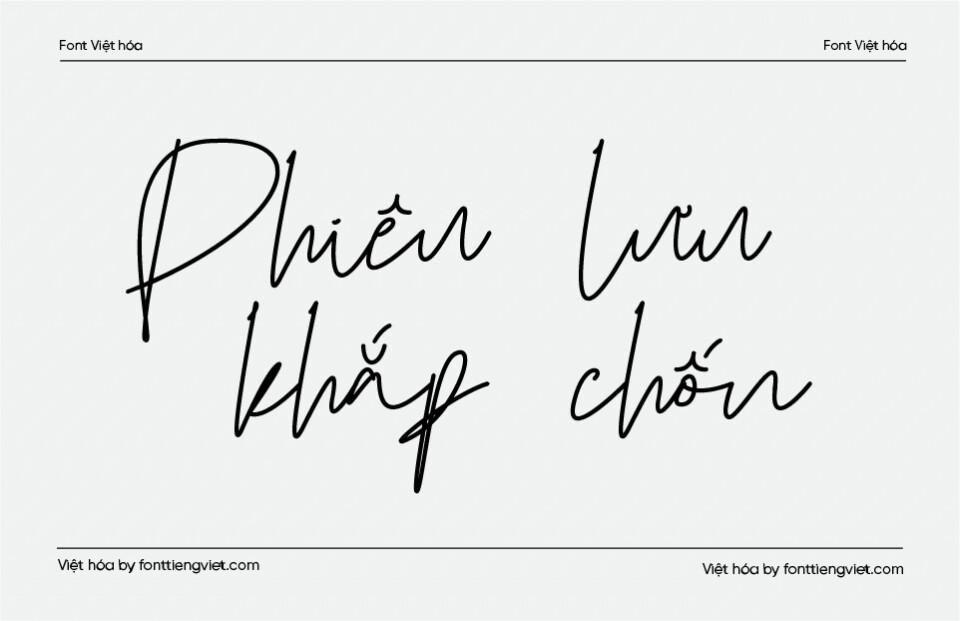
Trong thế giới thiết kế đồ họa, việc lựa chọn Font Chữ phù hợp có vai trò cực kỳ quan trọng, đặc biệt khi bạn muốn tạo ra sự tinh tế và cá nhân hóa cho các ấn phẩm đặc biệt. Đối với thiệp cưới, thiệp mời hay các tài liệu mang dấu ấn cá nhân, một font chữ viết tay đẹp mắt có thể nâng tầm giá trị thẩm mỹ lên một tầm cao mới. Và đó chính là lý do vì sao Font Việt hóa 1FTV VIP Kalmost – Chữ Ký Viết Tay Tinh Tinh Tế Cho Thiệp Cưới & Thiệp Mời lại trở thành lựa chọn hàng đầu của nhiều nhà thiết kế và cặp đôi. Font chữ này không chỉ mang đến vẻ đẹp mềm mại, uyển chuyển của nét chữ ký tay mà còn được Việt hóa hoàn chỉnh, đảm bảo trải nghiệm sử dụng mượt mà với ngôn ngữ tiếng Việt.
Khám Phá Sự Tinh Tế Của Font Việt hóa 1FTV VIP Kalmost – Chữ Ký Viết Tay Tinh Tế Cho Thiệp Cưới & Thiệp Mời
Bạn đang tìm kiếm một font chữ độc đáo, có khả năng thể hiện sự sang trọng, lãng mạn và mang đậm dấu ấn cá nhân? Font 1FTV VIP Kalmost chính là câu trả lời. Được thiết kế dựa trên cảm hứng từ những nét chữ ký tay tự nhiên, font chữ này sở hữu sự mềm mại, uyển chuyển khó cưỡng. Từng đường nét đều được chau chuốt tỉ mỉ, tạo nên một tổng thể hài hòa, dễ đọc nhưng vẫn giữ được chất nghệ thuật riêng. Đặc biệt, việc font được Việt hóa hoàn chỉnh là một điểm cộng lớn, giúp người dùng dễ dàng sử dụng tiếng Việt mà không gặp bất kỳ lỗi hiển thị hay mất ký tự nào. Điều này cực kỳ quan trọng đối với các ấn phẩm như thiệp cưới, thiệp mời sinh nhật hay các văn bản cần sự trang trọng, tinh tế.
Vì Sao Font 1FTV VIP Kalmost Được Ưa Chuộng Cho Thiệp Cưới?
Thiệp cưới không chỉ là lời mời mà còn là ấn tượng đầu tiên về ngày trọng đại của cặp đôi. Một chiếc thiệp cưới đẹp, độc đáo sẽ để lại dấu ấn khó phai trong lòng khách mời. Font 1FTV VIP Kalmost với phong cách chữ ký viết tay mang đến một cảm giác rất riêng, rất cá nhân, như chính cô dâu chú rể tự tay viết những lời mời chân thành nhất. Sự thanh lịch của font chữ này kết hợp hoàn hảo với các thiết kế thiệp tối giản hay cầu kỳ, tạo nên sự cân bằng hoàn hảo. Từ tên cô dâu chú rể, ngày tháng cho đến những câu trích dẫn lãng mạn, tất cả đều trở nên cuốn hút hơn khi được thể hiện bằng font Kalmost.
Ứng Dụng Đa Dạng Của Font Chữ Ký Viết Tay Kalmost
- Thiệp mời các sự kiện: Từ tiệc sinh nhật, kỷ niệm, khai trương đến các buổi hội thảo sang trọng, font Kalmost đều giúp thiệp mời của bạn trở nên đẳng cấp hơn.
- Thiết kế logo và thương hiệu: Đối với những thương hiệu muốn thể hiện sự độc đáo, cá nhân hóa và nghệ thuật, font chữ ký tay này là một lựa chọn tuyệt vời.
- Ấn phẩm cá nhân: Thư cảm ơn, danh thiếp cá nhân, chữ ký điện tử hay các dự án DIY (Do It Yourself) đều có thể trở nên ấn tượng hơn với Kalmost.
- Trang trí nội dung số: Các bài đăng mạng xã hội, poster quảng cáo, banner hoặc website cần một chút nét mềm mại, nghệ thuật cũng rất phù hợp với font này.
- Sách và ấn phẩm văn học: Tạo điểm nhấn cho tiêu đề, trích dẫn hoặc tên tác giả, mang lại cảm giác cổ điển và trang trọng.
Font Việt Hóa: Tầm Quan Trọng Và Lợi Ích
Việc một font chữ được Việt hóa không chỉ đơn thuần là thêm các dấu tiếng Việt. Nó là cả một quá trình điều chỉnh tỉ mỉ để các ký tự có dấu không bị lỗi, không bị vỡ nét và vẫn giữ được vẻ đẹp nguyên bản của font. Với Font Việt hóa 1FTV VIP Kalmost, bạn hoàn toàn có thể yên tâm sử dụng tiếng Việt một cách mượt mà, chuyên nghiệp cho mọi ấn phẩm của mình. Điều này đặc biệt quan trọng khi bạn muốn gửi gắm những thông điệp yêu thương, chân thành bằng tiếng mẹ đẻ trên các thiệp mời hay thiệp cưới.
Sở hữu một font chữ độc đáo như Kalmost giúp bạn tạo ra sự khác biệt, thể hiện cá tính riêng và nâng cao giá trị thẩm mỹ cho mọi dự án. Đây không chỉ là một công cụ thiết kế mà còn là một phương tiện để truyền tải cảm xúc và câu chuyện.
Tóm lại, Font Việt hóa 1FTV VIP Kalmost – Chữ Ký Viết Tay Tinh Tế Cho Thiệp Cưới & Thiệp Mời là một lựa chọn hoàn hảo cho những ai đang tìm kiếm sự độc đáo, sang trọng và cá nhân hóa trong thiết kế. Với vẻ đẹp mềm mại, uyển chuyển của nét chữ ký tay cùng khả năng Việt hóa tối ưu, font chữ này chắc chắn sẽ làm hài lòng cả những người dùng khó tính nhất. Hãy để Font Chữ này góp phần tạo nên những ấn phẩm thật sự ấn tượng và đáng nhớ cho các sự kiện quan trọng của bạn. Đừng bỏ lỡ cơ hội sở hữu và trải nghiệm sự khác biệt mà Kalmost mang lại!